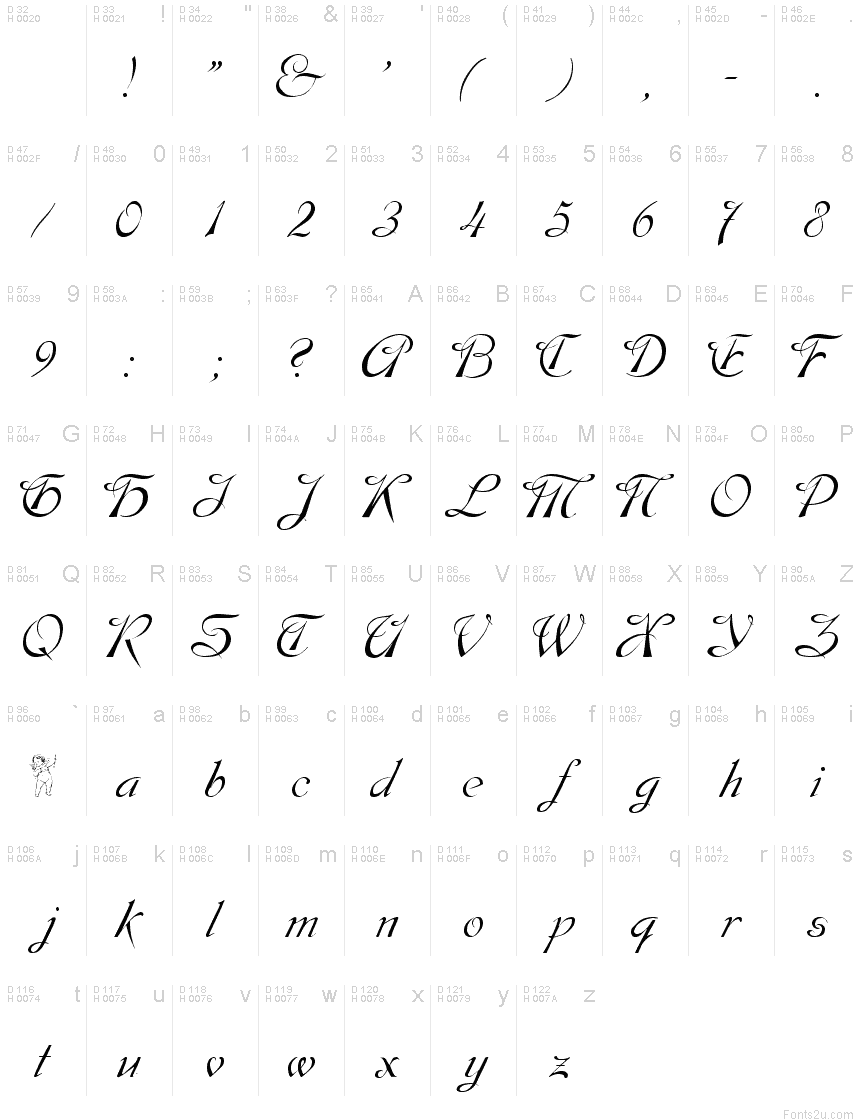
Dobkin Plain od D. Rakowskiego to darmowy krój kaligraficzny, który łączy pewny zamach stalówki z dramatyzmem odręcznego podpisu. Litery nachylają się w prawo, tworząc płynne, niemal płynne krzywe, które kończą się delikatnymi, zwężanymi akcentami – połączenie, które jest jednocześnie romantyczne i nieco teatralne. Płynny rytm rodziny Dobkin oraz eleganckie, zwarte odstępy nadają tekstowi charakter ciągłego pisma odręcznego, które nie sprawia wrażenia niechlujnego czy zbyt swobodnego.
Ten darmowy font świetnie sprawdza się w zaproszeniach ślubnych, papeterii okolicznościowej, certyfikatach, identyfikacji wizualnej butików, okładkach książek, etykietach na wino lub perfumy oraz eleganckich grafikach do mediów społecznościowych. Wyrafinowany, kaligraficzny charakter pisma natychmiast dodaje projektom odświętnego, uroczystego klimatu, zwłaszcza gdy jest użyty w dużym rozmiarze i z odpowiednim światłem między wierszami. Zestaw ten krój z lekkim, czystym fontem bezszeryfowym w tekście pomocniczym, aby zachować czytelność układu, pozwalając jednocześnie Dobkin Plain grać pierwsze skrzypce.